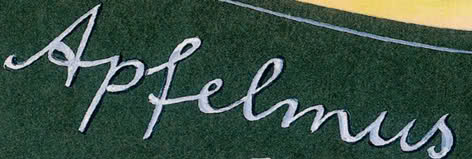
Welcher Font ist das?
ich darf eine Dokumentation für ein Kinderprojekt erstellen und suche dafür eine Schrift, die ungefähr so aussehen könnte.
Kennt die vielleicht jemand? Bzw. gibt es eine kostenlose Variante? Über einen Tipp würde ich mich sehr freuen.
Ich möchte bestimmte KinderZitate mit dieser Schrift besonders hervorheben. Die eigentliche Hausschrift ist Tondo. Könnt ihr mir sagen, ob das passt?
:P ich schau mir grad die Schrift... Ist wohl eher eine altdeutsche Schrift als eine Kinderschrift, oder?
Kennt die vielleicht jemand?
Klar. Viele von uns haben diese Lateinische Ausgangsschrift (LA) in der Schule gelernt. Nicht jeder hatte die vereinfachte Ausgangsschrift (VA), wie die hier bereits erwähnte FF-Schulschrift. Zuerst mal die Basisinformationen:
Bitte keine Learning Curve! Das ist Gringo-Schreib und ich muss jedesmal kotzen wenn so ein DTP-Flachmann damit für Doitsches Schulzeug wirbt.